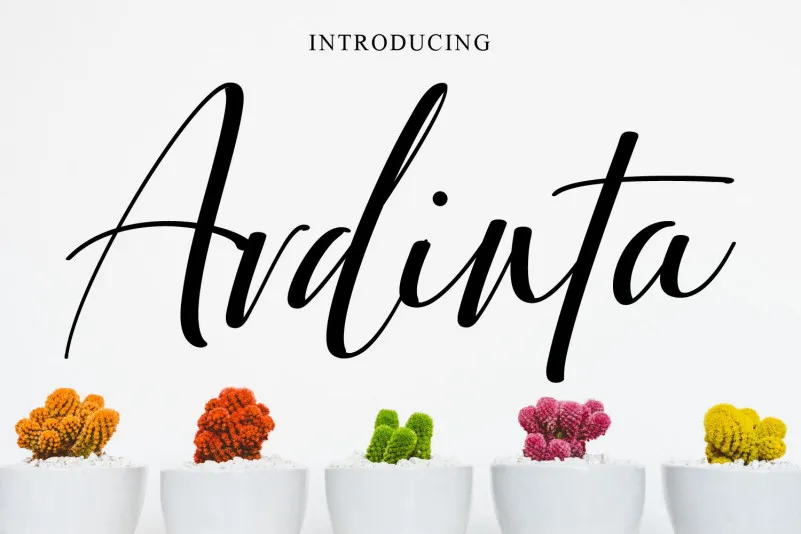
A Ardinta Font é uma fonte de escrita que encanta os olhos com seu estilo elegante e moderno. Sua design caracteriza-se por uma leveza única, criando um efeito atraente para nomes de marca ou cartazes. Este projeto foi criado pensando em uma variedade de aplicações, incluindo logotipos, identidades visuais, convites, decoração de papel, designs de casamentos, posts nas redes sociais e muito mais. A Ardinta oferece um equilíbrio perfeito entre tradicionalidade e modernidade que torna-a uma opção versátil para qualquer projeto. Seria o complemento ideal para criar designs únicos e sofisticados.